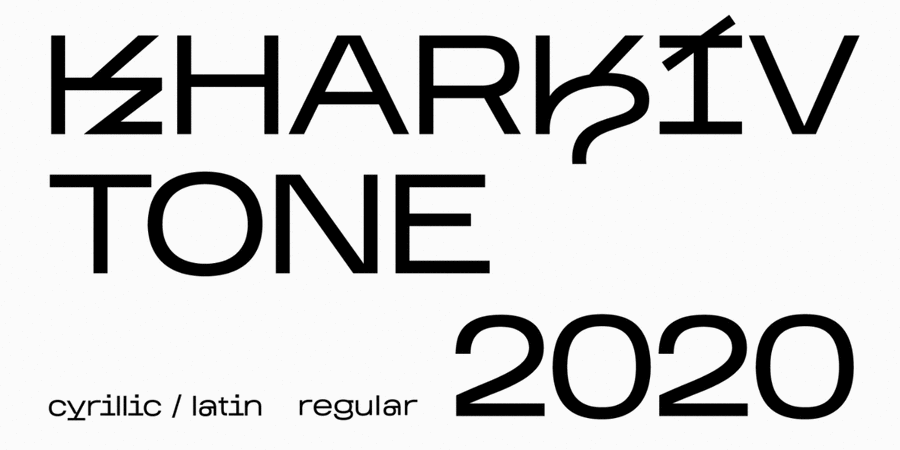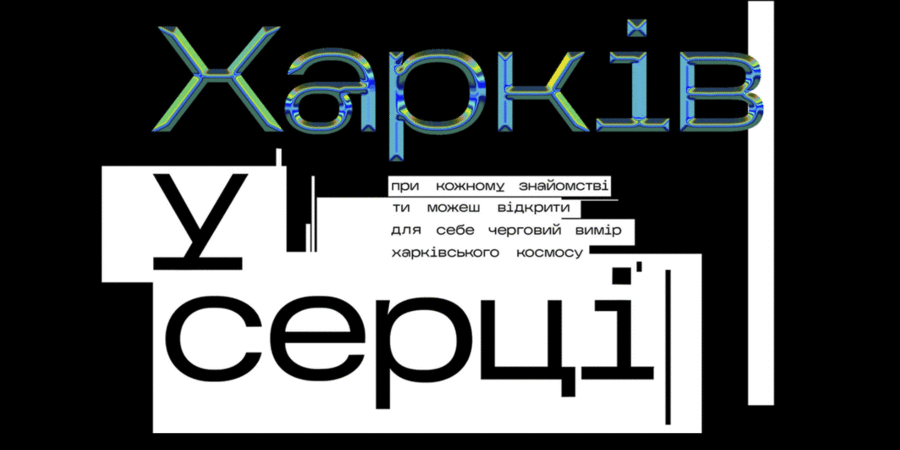
Харків – еклектичне місто, яке має свій настрій. Тут поєднується непоєднуване, як і у шрифті Kharkiv Tone. Літери натхненні графіті, технічними та рукописними шрифтами зі стін міста. Цей шрифт – голос Харкова. Тому Kharkiv Tone можна використовувати в якості основного елементу брендингу території. Шрифт розробила Катерина Дрозд у 2020 році.
Асоціації з сімейством шрифтів Kharkiv ToneОсобистість і характер гарнітури:
техногенний, футуристичний, незграбний, ламаний, прямокутний, твердий, стійкий, індустріальний, динамічний, урбаністичний, грубий, міцний, міський, сучасний, залізний, сталевий, різкий, чіткий, гострий, архітектурний, дивний, цікавий, самобутній, оригінальний, характерний, молодіжний, модний, вуличний, тусовочний, іронічний, грайливий, електронний, клубний, двіжняковий, експериментальний, яскравий, сміливий, рубаний, божевільний, потішний, незвичайний, прикольний, інопланетний, свіжий, скляний
інтернет, гаджет, девайс, коворкінг, дизайн, Місто, урбаністика, архітектура, меблі, архітектор, мода, нічний клуб, вечірка, наука, фантастика, гра, електроніка, розваги, тусовка, селфі, інтер'єр, конструктор, клуб, бар, анімація, квест, коктейль, туризм Гарнітура має ознаки стилів: